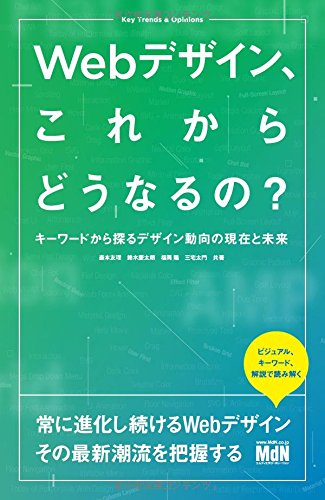
Webデザイン、これからどうなるの? キーワードから探るデザイン動向の現在と未来
Webデザインの第一線で活躍するクリエイターや識者である森本友理氏、鈴木慶太朗氏、福岡陽氏、三宅太門氏により、「最新のWebデザイン」と「これからのWebデザイン」について解説した「Webデザイン、これからどうなるの? キーワードから探るデザイン動向の現在と未来」がエムディエヌコーポレーションより2018年1月17日に発売されました。
さすがはこれからのWebデザインについて書かれた本書、早くもバリアブルフォント(Variable Font)も取り上げられている。
バリアブルフォント(Variable Font)
▲Adobe Typekit Blogより引用
従来のフォントが標準とBOLD(太字)の2種類のウェイトしか使えず、それ以上に細いストロークもしくは太いストロークを使用したい場合は同じフォントファミリーの別フォントを用意する必要があったが、Microsoft、Google、Adobe、Appleらが共同で開発した新しい仕組みのフォント「バリアブルフォント(Variable Font)」では、1つのフォントファイルでありながらユーザーがウェイトを自由に変更できる。ウェイトを変更しても文字幅が変わらないためレイアウトの変更が不要になるというメリットやウェイトを変えられるためファイルサイズも小さいといった利点がある。
将来的には静的フォントが「Variable Font」に置き換わることも期待されている。
Webサイトはモバイルで閲覧できることが当たり前となり、動画や3Dコンテンツもブラウザー上でストレスなく楽しめるようになりました。ニュースや新製品のプロモーション、音楽や動画ストリーミングまで、私たちは日夜膨大な情報をWebサイトを介して得ています。コンテンツの多様化に伴い、素早く情報を得られる実用的でユーザービリティの高いインターフェースが求められるときもあれば、ひと目でブランドのファンにさせるような魅力的で感情に訴えかける表現が求められるときもあるでしょう。移動中はスマートフォンで、職場や自宅ではラップトップやタブレットでと、生活によって情報の受け取り方もさまざまです。Webデザインは技術の進歩だけでなくライフスタイルやカルチャーの変化とも相互に影響を及ぼしながら進化を続けているのです。
「ユーザーを迷わせない情報設計」「心地よい配色」「読みやすいタイポグラフィ」といった普遍的なスキルを学習することはもちろん重要ですが、環境の進歩・変化に最適化されたユーザー体験を生み出すためには最新のデザイントレンドや技術をキャッチアップすることも欠かせません。
(本書「はじめに」より)
「UI」「レイアウト」「グラフィック」「タイポグラフィ」「配色」の5つをテーマに、さまざまな手法で作られた実例とその意義・効果を知ることで、Webデザインの最前線、そしてこれから流行るであろうデザインの傾向を一望できます。また各分野の第一線で活躍するクリエイターや識者が、「いま」のWebデザインに対する独自の意見や見解を交えながら執筆した「オピニオンコラム」も掲載しています。